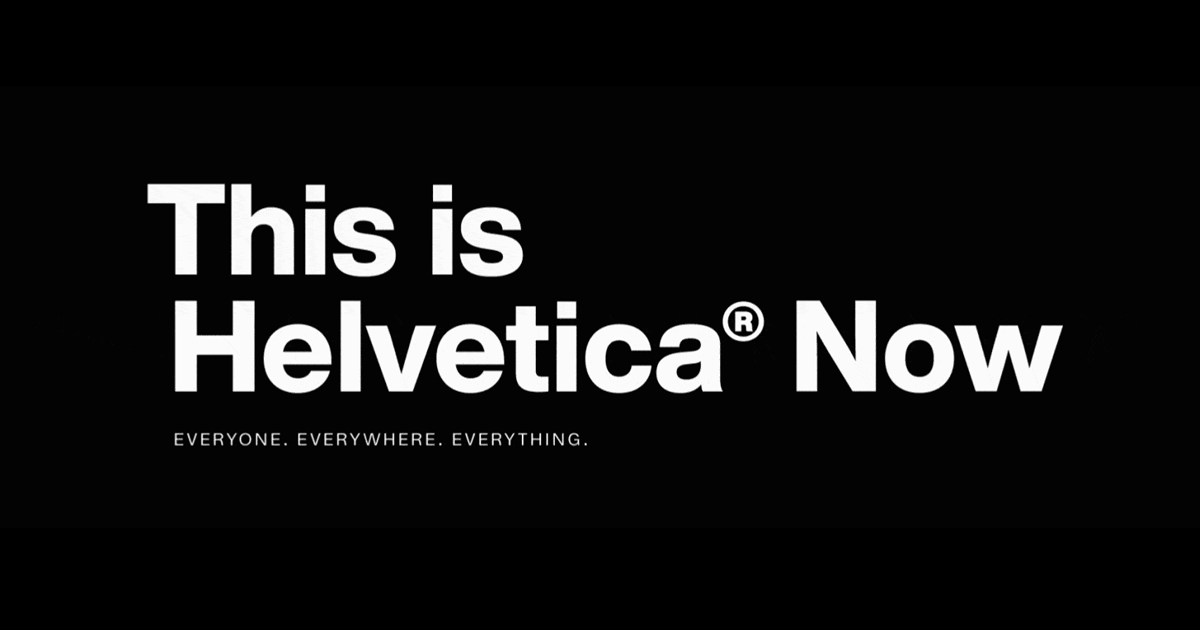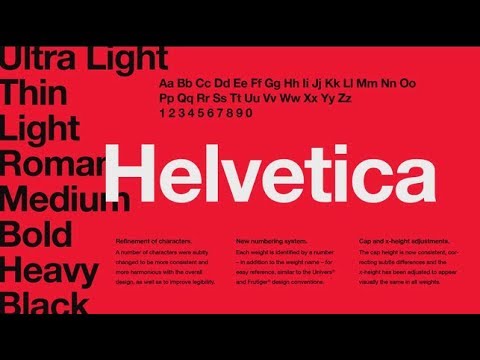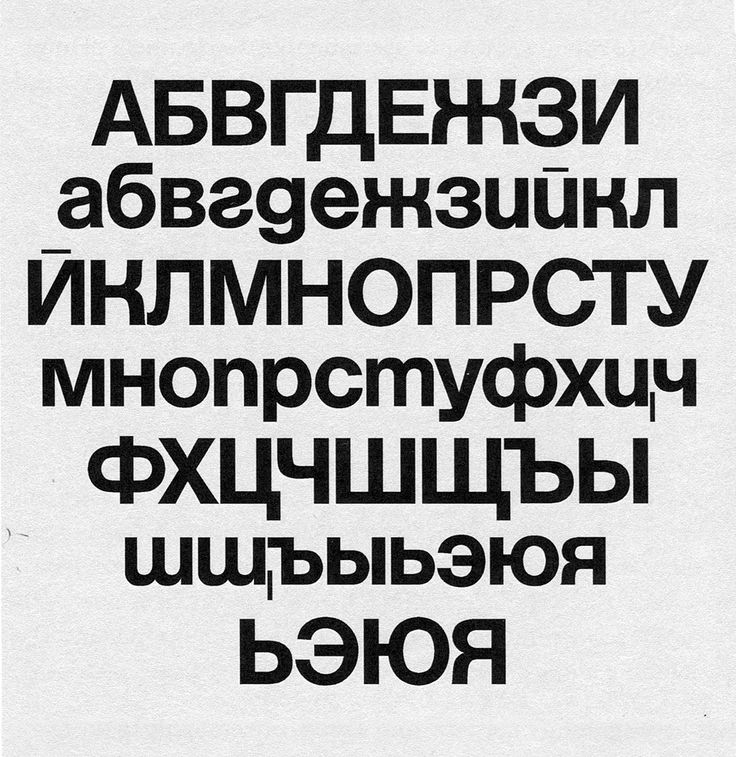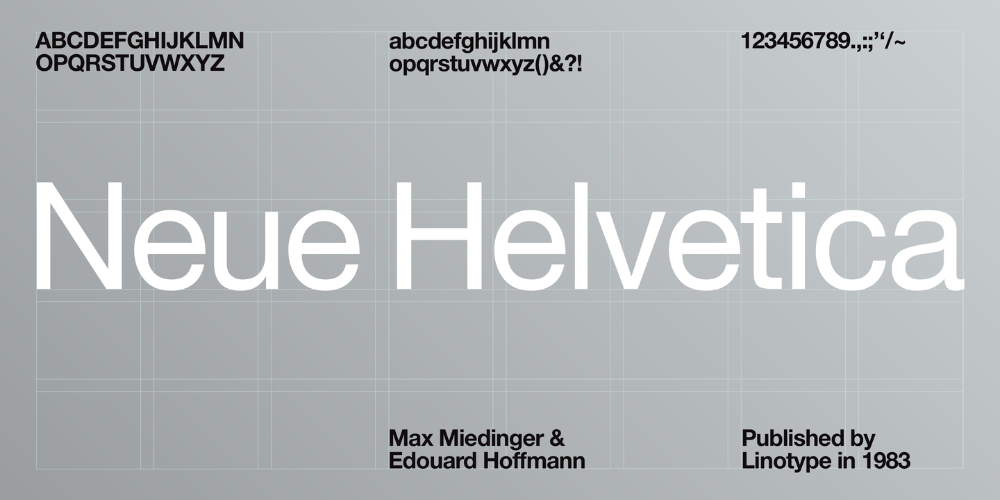
Расширение Sans — шрифт Serif, Helvetica шрифта приобрели особое значение, потому что ее разборчивости. Это очень легко читать текст, когда этот стиль будет выбран. Первоначально разработанная в Швейцарии, это имеет сейчас много вариантов на выбор, и некоторые из них включают свет, узкие, округлые, сжатые, учебник, и т.д. Чем она отличается от других является то, что он может быть использован для различных целей. Ясность шрифта делает его идеальным для личного, а также профессионального использования. Будь то проекты, презентации или электронные письма, нет ничего практичнее, чем Helvetica Font. Пользователи могут проверить бесплатные пачек данном шрифта, который можно скачать на ПК и ноутбуках. С нескольких сотен вариантов на выбор, это бесплатный инструмент может оказаться очень удобным для всех тех, кто ищет то же самое. Это факт, что различные стили вышеупомянутого шрифта используются в отдельных частях мира. Таким образом, пользователи могут выбрать те, которые занимают видное место в своем регионе и сделать большую часть этого стиля.![]()